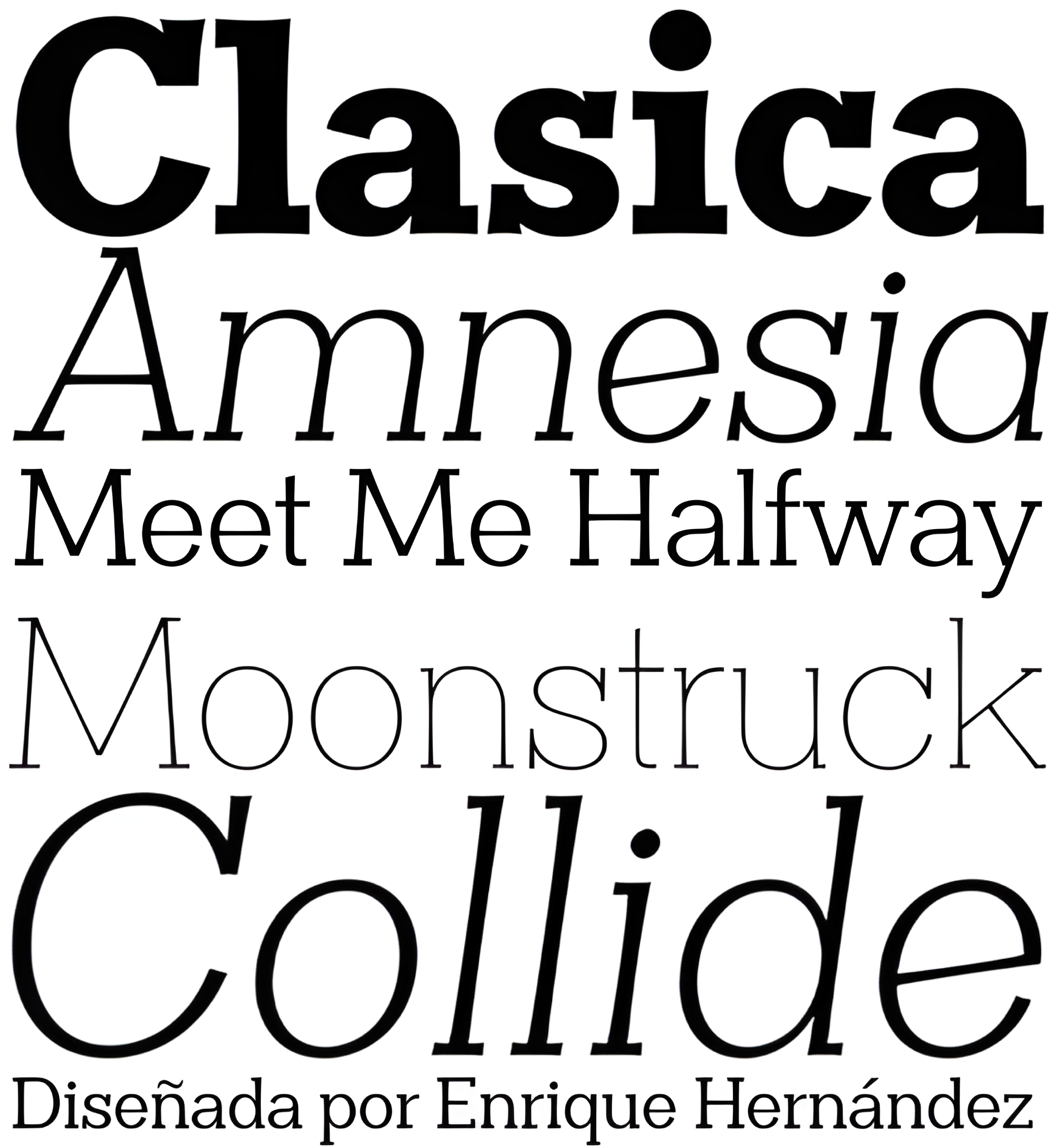
| Año | 2014 |
| Créditos | Enrique Hernández |
| Descripción | La familia tipográfica «Clasica»"; es ideal para cubrir cualquier necesidad de diseño. Excelente para títulos, párrafos, revistas, libros, editoriales y logotipos. La particularidad e identidad de esta fuente se encuentra en la delgadez de sus trazos verticales y su gracias simétricas. Inspirada en la fuente «Optima»; pero con un serif que le da un toque diferente y nuevo. «Clasica»; cuenta con glifos para las letras: a, e, f, g, r e y. Esta familia tipográfica viene con 9 pesos diferentes con sus respectivas cursivas. |
| Familia(s) | Thin, Thin Italic, Light, Light Italic, Book, Book Italic, Regular, Regular Italic, Medium, Medium Italic, Bold, Bold Italic, Heavy, Heavy Italic, Black, Black Italic, UltraBlack, UltraBlack Italic |
| Estilos | 18 |